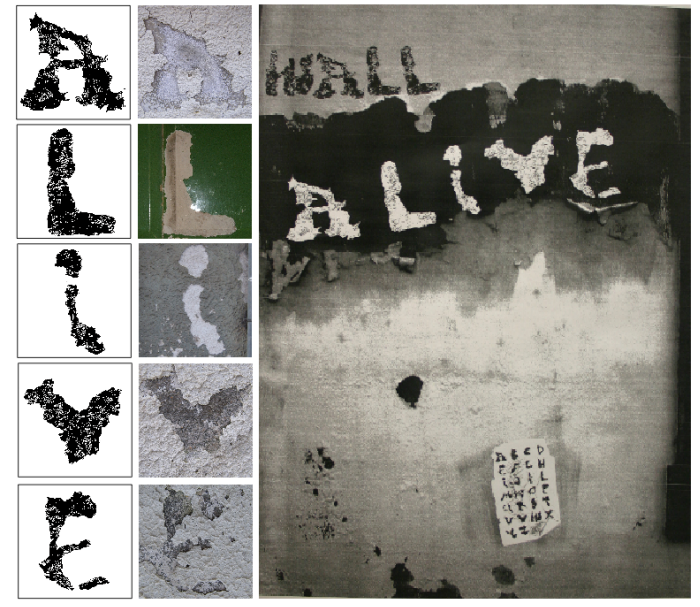
alfabeto - foi realizada uma recolha fotografica de todas as letras do alfabeto em descascamentos de parede. Estas foram trabalhadas de forma a conseguirem ser legiveis e ainda a manterem algum vestigio da sua origem, neste caso a textura da letra.
Posteriormente fez-se um cartaz que mostra-se a origem da tipografia assim como todas as letras que a compoem.